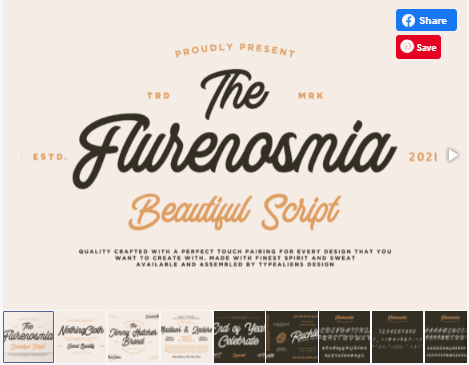
Flurenosmia Font
FLURENOSMIA - очень красивый шрифт с аккуратными формами, похожими на монолинии, но со слегка острыми концами штрихов. Он подходит для элегантного и современного брендинга и подходит для дизайна вашего бренда в социальных сетях. Его также можно использовать для дизайна свадебных приглашений или других дизайнов, требующих изящного и красивого стиля.